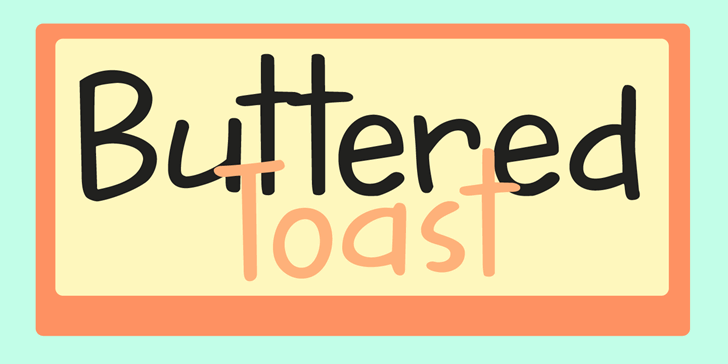
A DK Buttered Toast é uma tipografia sans-serif criada por Hamilton em 2015. Esta é a versão demo básica do famoso ‘Buttered Toast’. Ela é gratuita para uso pessoal. Se você pretender usar na produção comercial, deve adquirir a versão completa que inclui kerning, direitos de embedding, todos os glifos e extras disponíveis em meu site: hanodedfonts.com. Não se esqueça de verificar as condições específicas antes de comprá-la, pois não é permitido seu uso em jogos, apps ou softwares. Se você está procurando por uma fonte leve e descontraída para seus projetos digitais, a DK Buttered Toast será certamente um bom ponto de partida. Ela possui uma aparência suave e confortável, que se adapta perfeitamente tanto para textos legíveis quanto para gráficos divertidos. Não hesite em explorar mais o site do Hamilton: hanodedfonts.com, onde você encontrará uma variedade de fontes inspiradoras e versáteis.